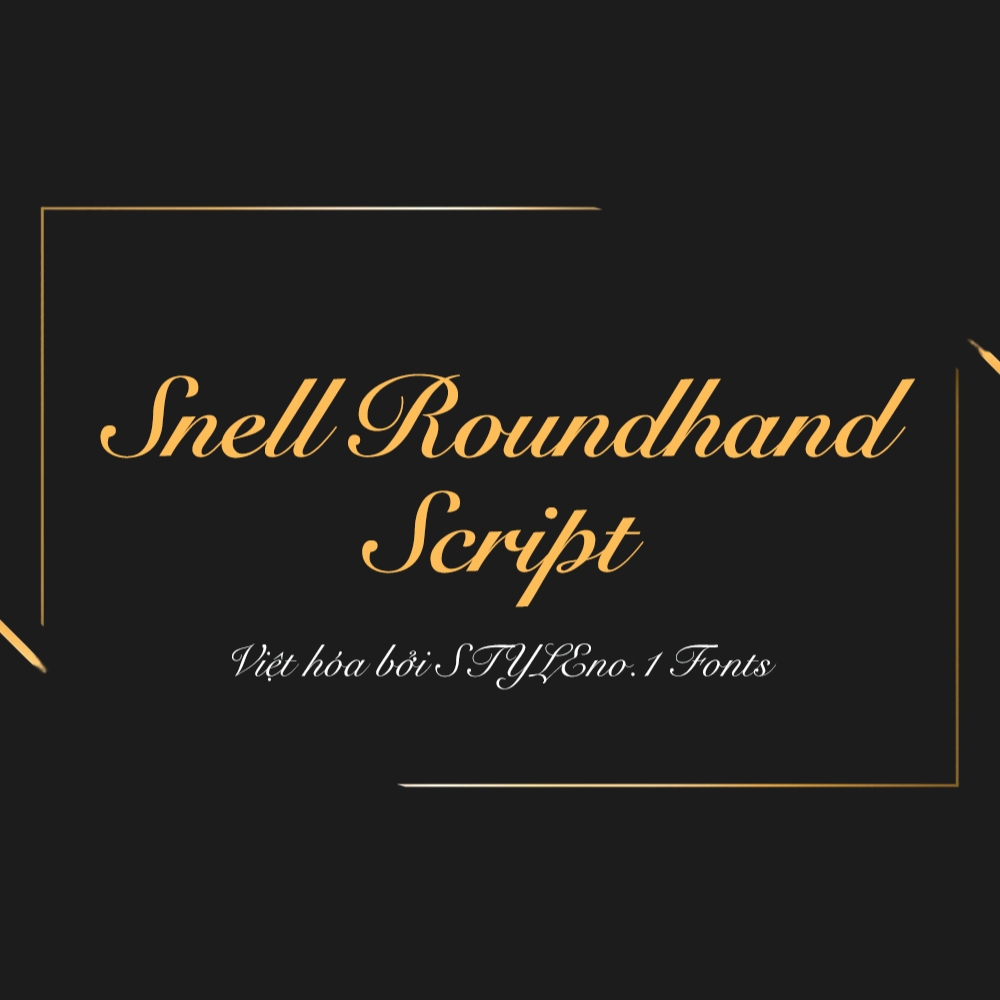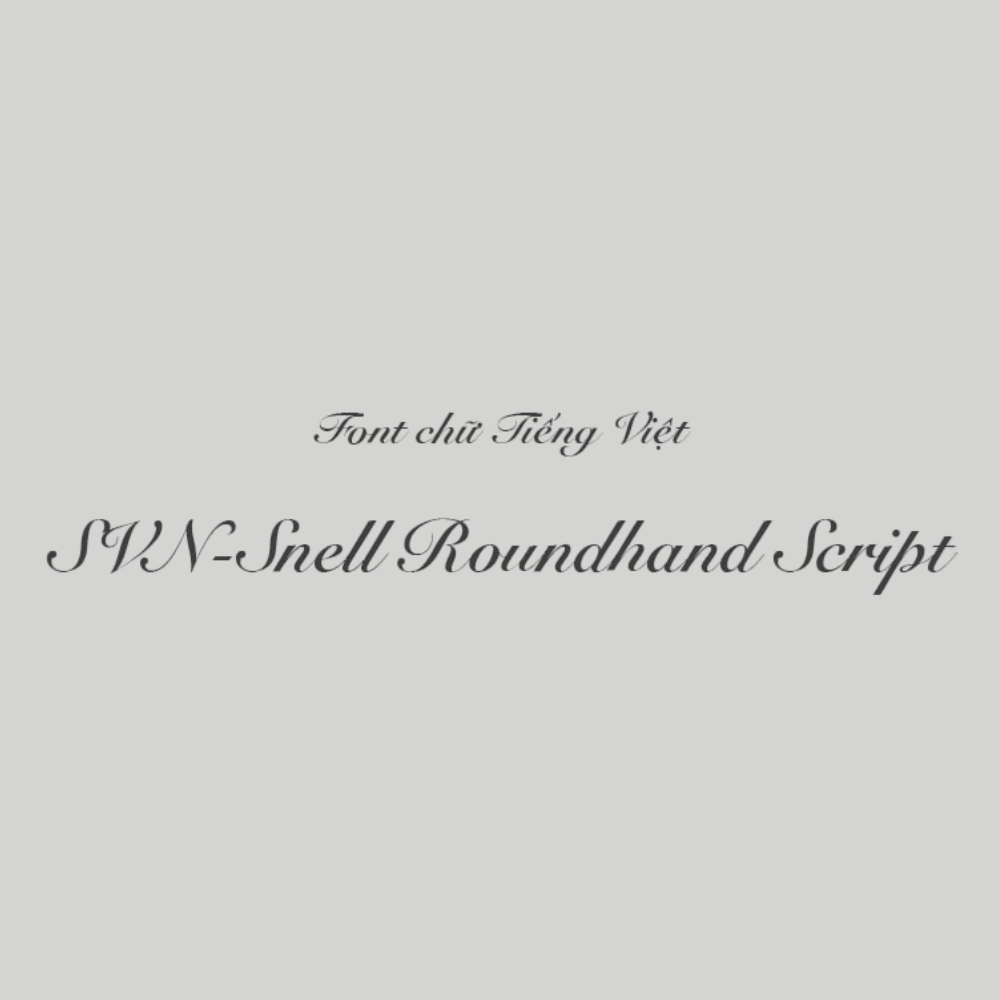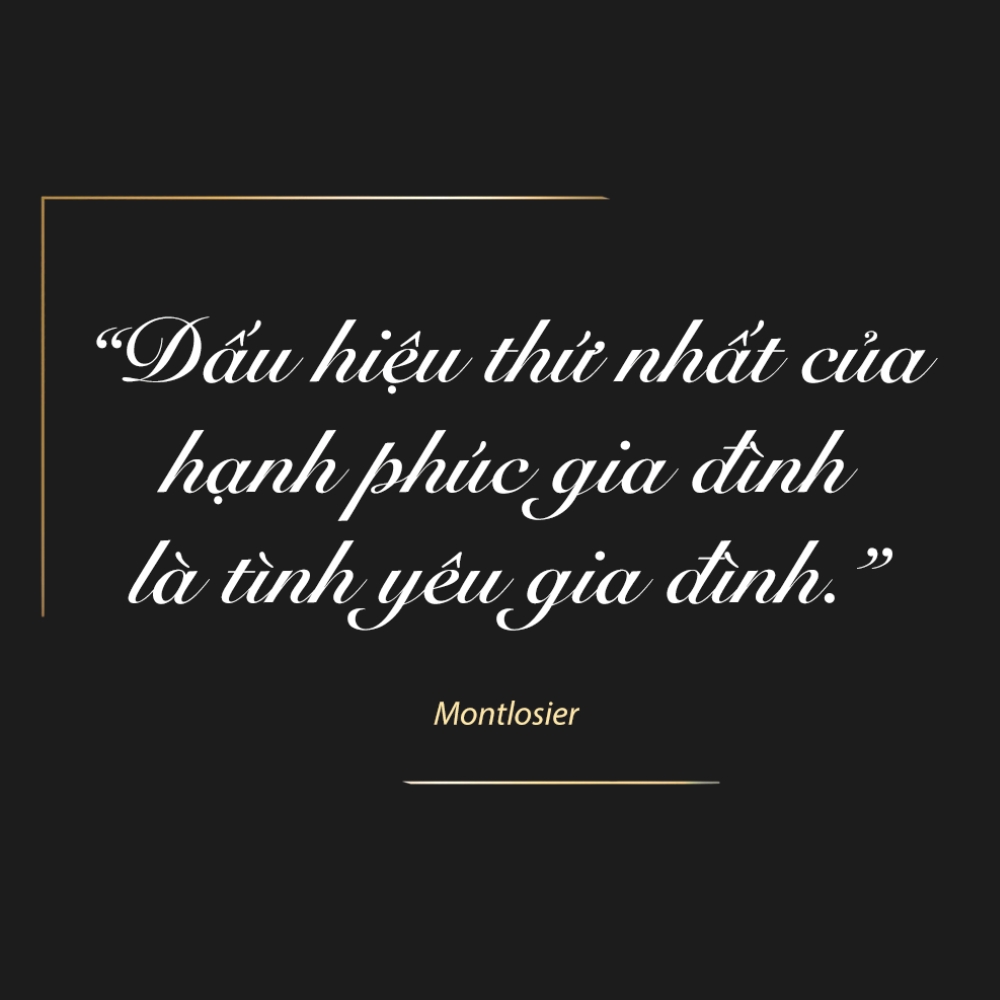
Font Việt hóa SVN Snell Roundhand Script là font chữ thư pháp viết tay thanh lịch phong cách Anh cổ điển được sử dụng rộng rãi trong thiết kế thiệp cưới cao cấp, thiệp mời sự kiện và bao bì quà tặng luxury. Font chữ tiếng việt SVN-Snell Roundhand Script mang nét chữ cursive liền mạch, trang nhã phù hợp cho sản phẩm cao cấp.
Font Việt hoá SVN Snell Roundhand Script là gì?
Font Việt hóa SVN Snell Roundhand Script được thiết kế dựa trên nét chữ viết tay roundhand của thế kỷ 17-18 tại Anh. Roundhand (hay còn gọi là English Roundhand) là phong cách viết thư pháp phổ biến trong giới thượng lưu Anh, được sử dụng cho các văn bản quan trọng, thư từ chính thức và tài liệu pháp lý.
Font Snell Roundhand mang những đặc điểm:
- Nét viết cursive liền mạch: Các chữ cái nối với nhau tự nhiên, tạo dòng chữ chảy như viết tay thật.
- Thanh lịch, cổ điển: Phong cách thư pháp Anh trang nhã, phù hợp sự kiện formal.
- Độ nghiêng vừa phải: Nét chữ nghiêng nhẹ tạo sự uyển chuyển nhưng vẫn dễ đọc.
- Nét dày-mảnh rõ ràng: Các nét xuống đậm, nét lên mỏng theo kiểu viết ngòi bút lông cổ điển.
SVN Snell Roundhand Script là phiên bản việt hóa, hỗ trợ đầy đủ dấu thanh tiếng Việt (á, à, ả, ã, ạ, ă, ắ…) để sử dụng cho thiệp cưới, thiệp mời tiếng Việt.
Các phiên bản Snell Roundhand thường gặp:
- Snell Roundhand Regular: Phiên bản tiêu chuẩn, thanh lịch.
- Snell Roundhand Bold: Phiên bản đậm hơn, nổi bật hơn.
- Snell Roundhand Black: Phiên bản rất đậm, sử dụng cho tiêu đề lớn.
Bảng thông tin font SVN Snell Roundhand Script:
Phiên bản |
Font weight |
Ứng dụng in ấn |
SVN Snell Roundhand Regular |
400 | Nội dung thiệp cưới, thông tin sự kiện. |
SVN Snell Roundhand Bold |
700 | Tên cô dâu chú rể, tiêu đề thiệp mời. |
SVN Snell Roundhand Black |
900 | Logo sự kiện, tiêu đề lớn backdrop. |
Ứng dụng của font Việt hóa SVN Snell Roundhand Script
Font Việt hóa SVN Snell Roundhand Script được ưa chuộng trong sản phẩm cao cấp:
- Tạo cảm giác sang trọng, trang trọng: Font script thư pháp gợi liên tưởng đến thư từ tay quý족, sự kiện formal, đẳng cấp thượng lưu.
- Phù hợp sự kiện quan trọng: Đám cưới, lễ kỷ niệm, gala dinner, tiệc VIP – những dịp đòi hỏi sự trang nhã.
- Kết hợp tốt với vàng, bạc: Font script hài hòa với chi tiết ép kim vàng, bạc, tạo thiệp mời luxury.
- Cân đối với font serif: Thường kết hợp: tiêu đề dùng script (tên cô dâu chú rể), nội dung dùng serif (thông tin chi tiết).
Font script Snell Roundhand-style xuất hiện trong nhiều sản phẩm in ấn:
- Thiệp cưới cao cấp: thiệp cưới truyền thống, thiệp cưới luxury, save the date.
- Thiệp mời sự kiện: gala dinner, anniversary, grand opening, VIP event.
- Menu nhà hàng fine dining: menu khách sạn 5 sao, nhà hàng Michelin.
- Bao bì quà tặng cao cấp: hộp quà tặng luxury, gift voucher, certificate.
- Nhãn sản phẩm premium: rượu vang, chocolate cao cấp, mỹ phẩm luxury.
- Catalogue thời trang cao cấp: lookbook haute couture, luxury brand.
- Certificate, diploma: bằng khen, chứng nhận, giấy khen trang trọng.
- Name card cao cấp: card giám đốc, card luật sư, card kiến trúc sư.
1. Font Việt hóa SVN Snell Roundhand Script có miễn phí không?
Font SVN việt hóa từ Snell Roundhand gốc. Để an toàn pháp lý, nên dùng font thay thế miễn phí như Dancing Script, Great Vibes từ Google Fonts – phong cách tương tự và hoàn toàn miễn phí.
3. Có nên dùng toàn bộ thiệp bằng font script không?
Không nên. Nên kết hợp: tiêu đề/tên người dùng script (nổi bật, thanh lịch), nội dung chi tiết dùng serif hoặc sans-serif (dễ đọc). Font script dùng nhiều sẽ khó đọc.